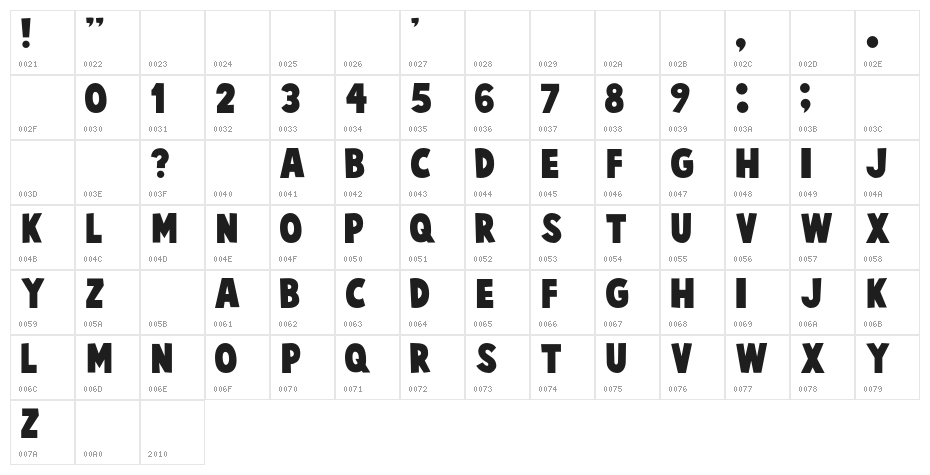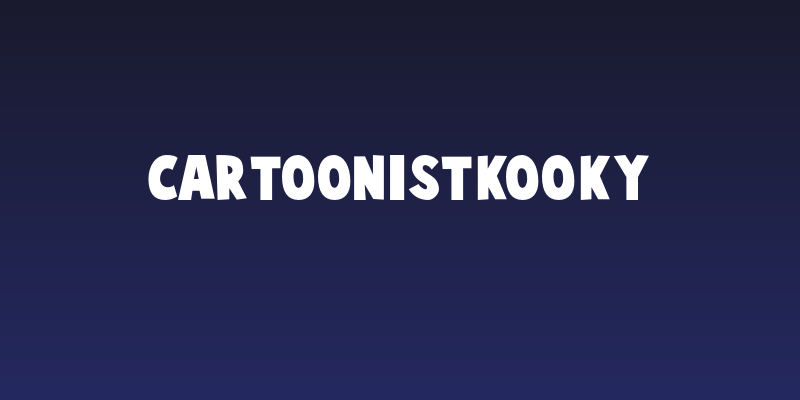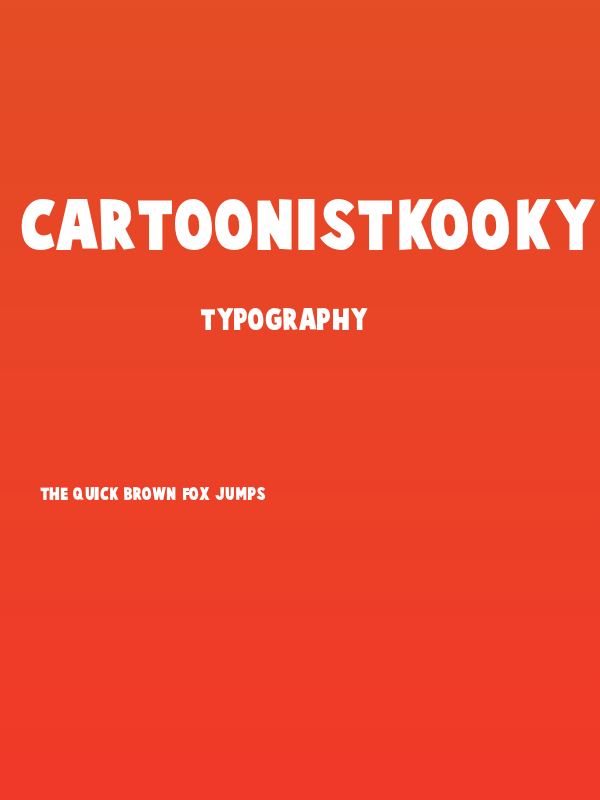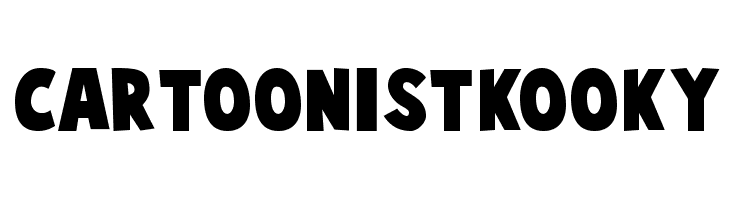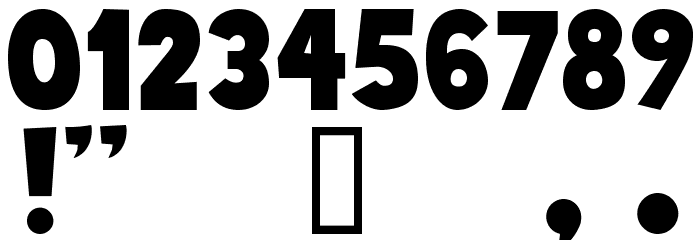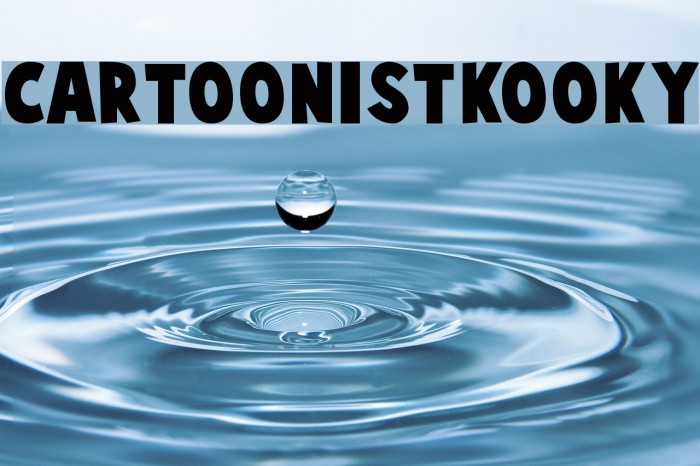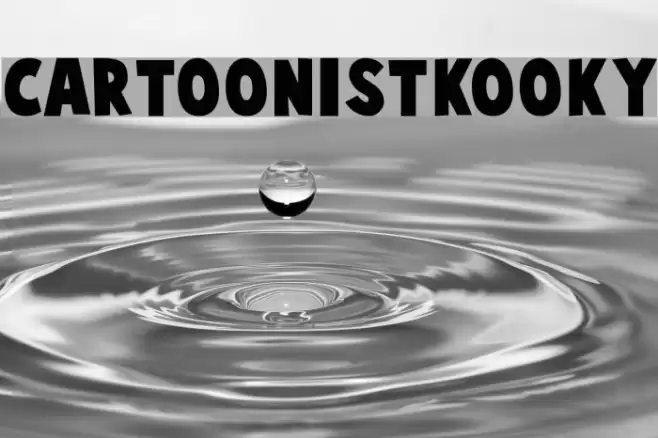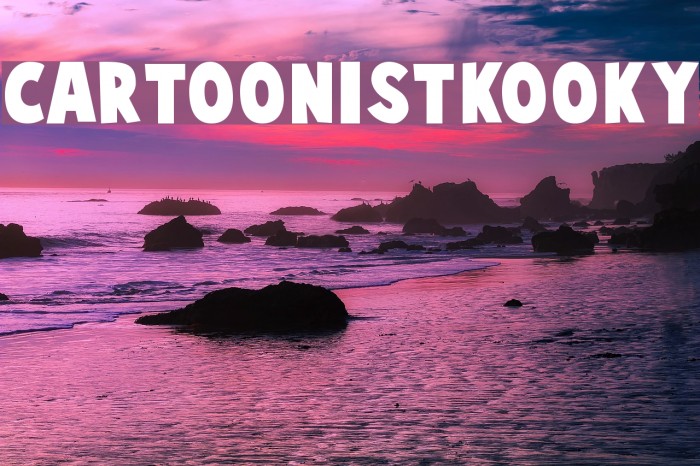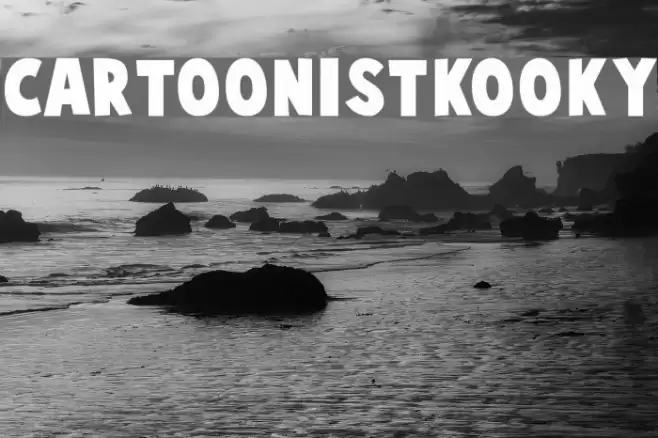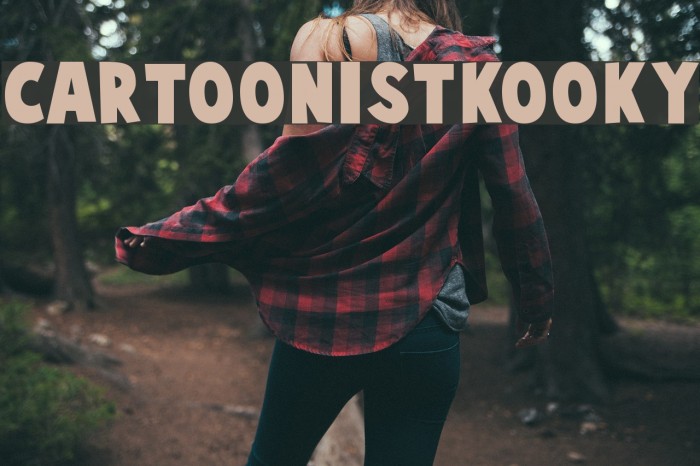
CartoonistKooky Font
| Stile generale | Playful, Whimsical |
| Progetti proposti | Ideal for children's books, comic strips, playful branding, and eye-catching posters. |